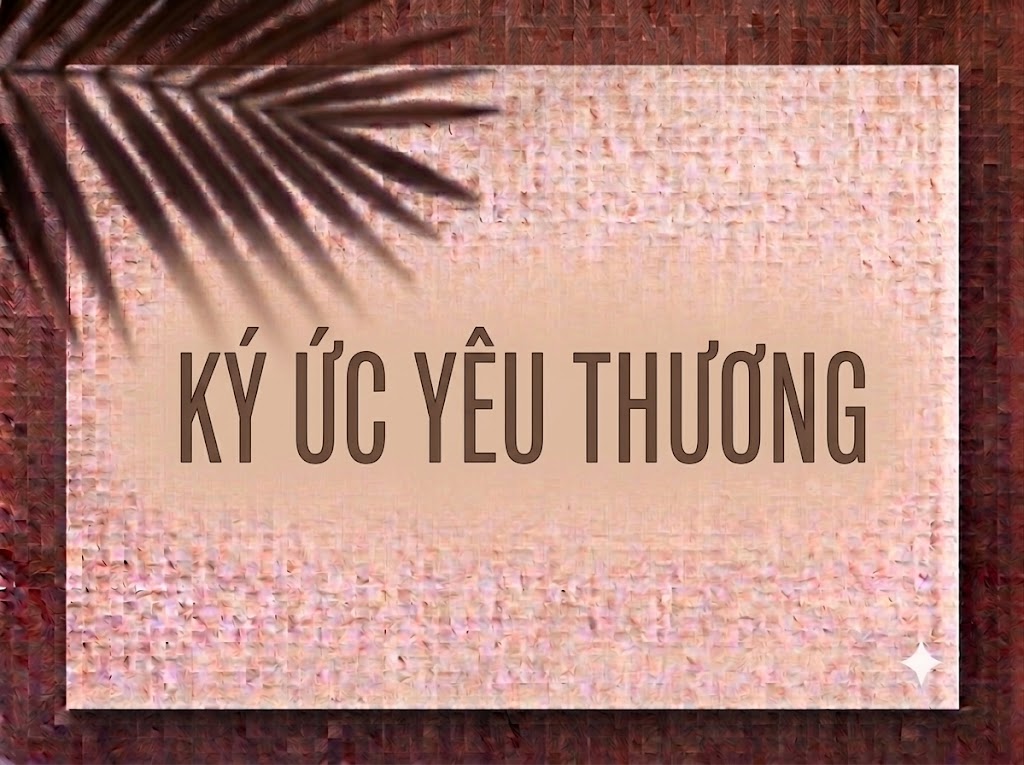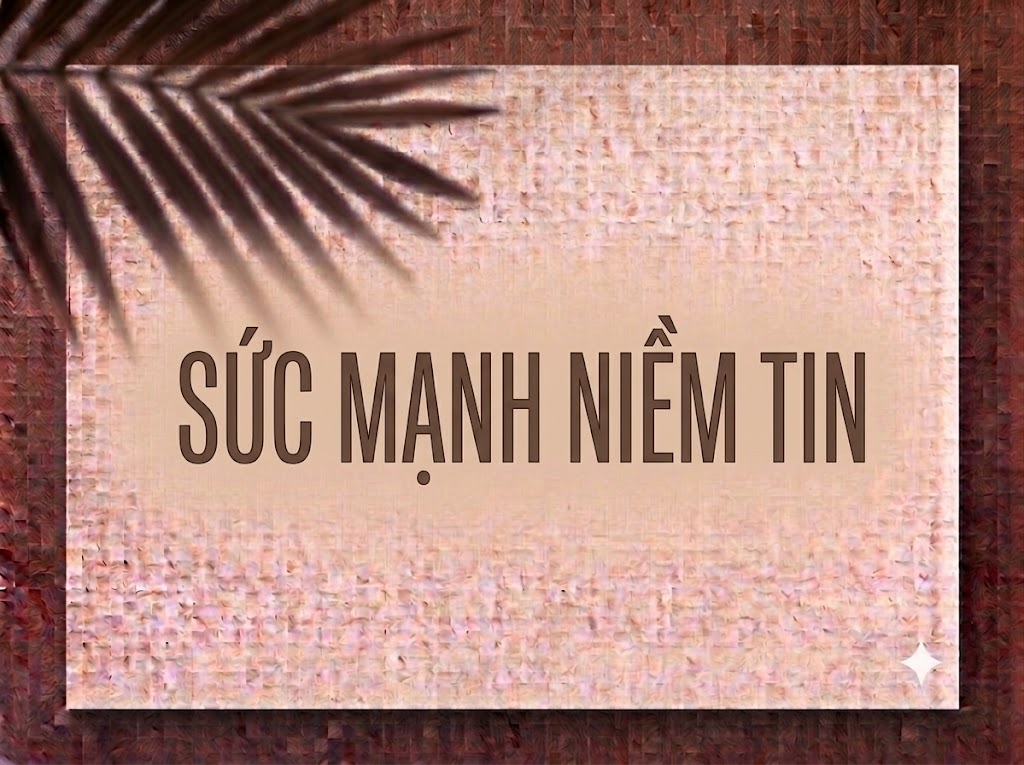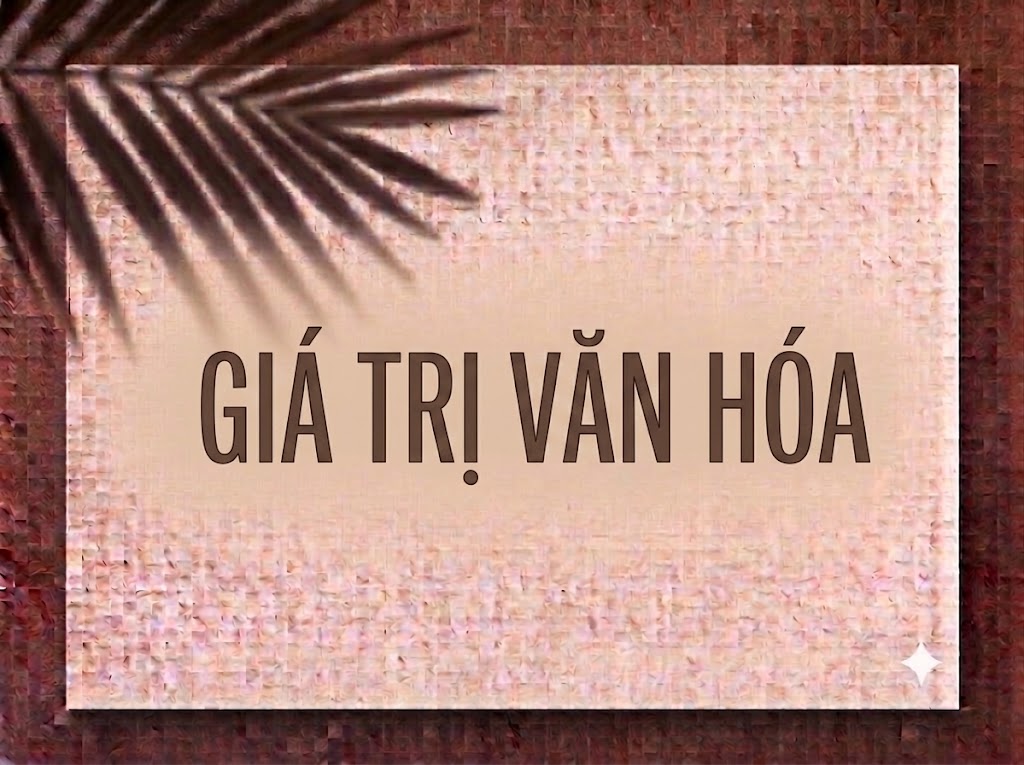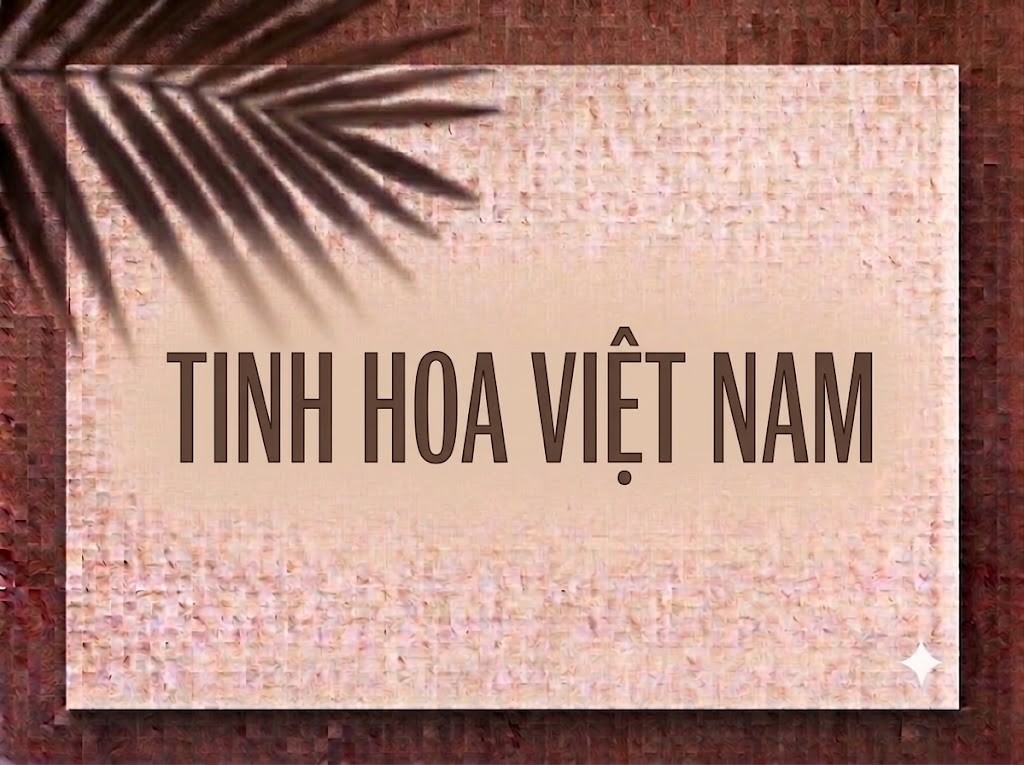
1FTV East Gravton
Sự kết hợp giữa phom dáng vươn cao (condensed) và tỷ lệ tương phản thanh đậm cực hạn luôn là công thức kinh điển để tạo nên những ấn phẩm truyền thông mang chuẩn mực Tạp chí (Editorial) và Thời trang cao cấp. Một dòng tiêu đề sở hữu đường nét kiêu kỳ không chỉ thu hút thị giác người xem ngay lập tức mà còn nâng tầm đẳng cấp thương hiệu.
Nếu bạn đang tìm kiếm một phông chữ Serif thanh lịch, sở hữu phom dáng cao ráo để làm bìa tạp chí, lookbook thời trang, logo luxury hay tiêu đề video ngắn, font 1FTV East Gravton chính là sự lựa chọn vô cùng hoàn hảo.
Giới thiệu về font 1FTV East Gravton
Font 1FTV East Gravton là bộ chữ hiển thị có chân (display serif) mang phong cách Modern Didone thanh lịch, nổi bật với sự giao thoa kịch tính giữa các cột nét dọc dày dặn và nét ngang mảnh mai:
Tên phông chữ: 1FTV East Gravton
Nhờ nền tảng kỹ thuật chỉn chu, phông chữ mang lại khả năng hiển thị vô cùng sắc nét. Bạn có thể tự tin phóng lớn chữ trên các ứng dụng thiết kế chuyên nghiệp hay phần mềm dựng video di động mà không lo vỡ nét hay răng cưa.
Đặc điểm nổi bật của phong cách thiết kế East Gravton
Sức hút thị giác của font 1FTV East Gravton đến từ tỷ lệ phom dáng kiêu sa cùng cấu trúc hình khối ấn tượng:
Tương phản thanh đậm Didone kịch tính: Sự chênh lệch rất lớn giữa thân chữ kiên cố và các nét ngang hairline mỏng như tơ mang lại chiều sâu nghệ thuật xa xỉ, gợi nhớ đến bìa các tạp chí hàng đầu như Vogue hay Harper’s Bazaar.
Phom dáng condensed vươn cao: Cấu trúc chữ thuôn dài giúp bạn thoải mái chèn những câu tiêu đề nhiều từ vào không gian hẹp mà vẫn đảm bảo cỡ chữ lớn, nổi bật và tiết kiệm diện tích ngang.
Hỗ trợ đồng bộ chữ hoa và chữ thường: Sự kết hợp hoàn hảo giữa dàn chữ in hoa vững chãi và bộ chữ thường thanh thoát giúp các nhà thiết kế dễ dàng phân tầng thông tin và tạo nhịp điệu chữ tự nhiên.
Để phông chữ vận hành mượt mà trên cả hệ điều hành Windows lẫn macOS, phiên bản này đã được tinh chỉnh kỹ lưỡng về mặt thông số nội tại:
Khoảng cách giữa các chữ (kerning) và độ giãn dòng được tính toán chuẩn xác, giúp các đường nét mảnh khi đứng cạnh nhau không bị dính nét hay mất chi tiết.
Tích hợp trọn vẹn bộ chữ cái hoa – thường, dãy chữ số 0-9 dáng đứng thanh lịch cùng hệ thống ký tự đặc biệt, dấu câu thông dụng.
Bản Việt hóa chuẩn chỉnh giúp bạn hoàn toàn yên tâm thiết kế các văn bản tiếng Việt có dấu mà không gặp lỗi nhảy font hay mất ký tự.
Hình ảnh demo thực tế của font 1FTV East Gravton
Khả năng hiển thị của phông chữ này được tối ưu rất tốt trên nhiều tỷ lệ kích thước khác nhau:
Kích thước nhỏ (12pt – 24pt): Cấu trúc chữ đứng ngay ngắn và khoảng hở nội tại thông thoáng giúp các câu chữ và dãy số vẫn hiển thị rõ ràng trên màn hình di động.
Kích thước lớn (36pt – 72pt): Đây là đất diễn lý tưởng nhất để 1FTV East Gravton phô diễn toàn bộ vẻ kiêu sa, sang trọng của các đường nét Didone tương phản, tạo tác động thị giác mạnh mẽ cho các dòng tiêu đề chính.
Ứng dụng trong thiết kế đồ họa và làm video
Sở hữu nét cá tính sang trọng và chuẩn mực Tạp chí, font 1FTV East Gravton mở ra không gian ứng dụng phong phú:
Video ngắn (TikTok, Reels, Shorts): Phông chữ serif dáng cao này hiển thị rất đẹp trên khung hình đứng tỷ lệ 9:16, cực kỳ ăn nhập với các video vlog thời trang, review mỹ phẩm, trang sức hay phong cách sống nghệ thuật.
Ảnh thu nhỏ YouTube (Thumbnail): Lựa chọn tuyệt vời cho các kênh làm nội dung về thời trang, làm đẹp, âm nhạc lofi, acoustic hoặc review đồ hiệu nhờ giao diện chuyên nghiệp và thu hút.
Thiết kế Bìa Tạp chí, Lookbook và Poster: Hoàn hảo cho các sản phẩm truyền thông thuộc lĩnh vực thời trang thiết kế, spa, mỹ phẩm, triển lãm nghệ thuật hay thương hiệu váy cưới.
Nhận diện thương hiệu phân khúc Luxury: Thích hợp làm logo dạng chữ, bao bì nước hoa, menu nhà hàng/khách sạn 5 sao hay thiệp mời sự kiện VIP.